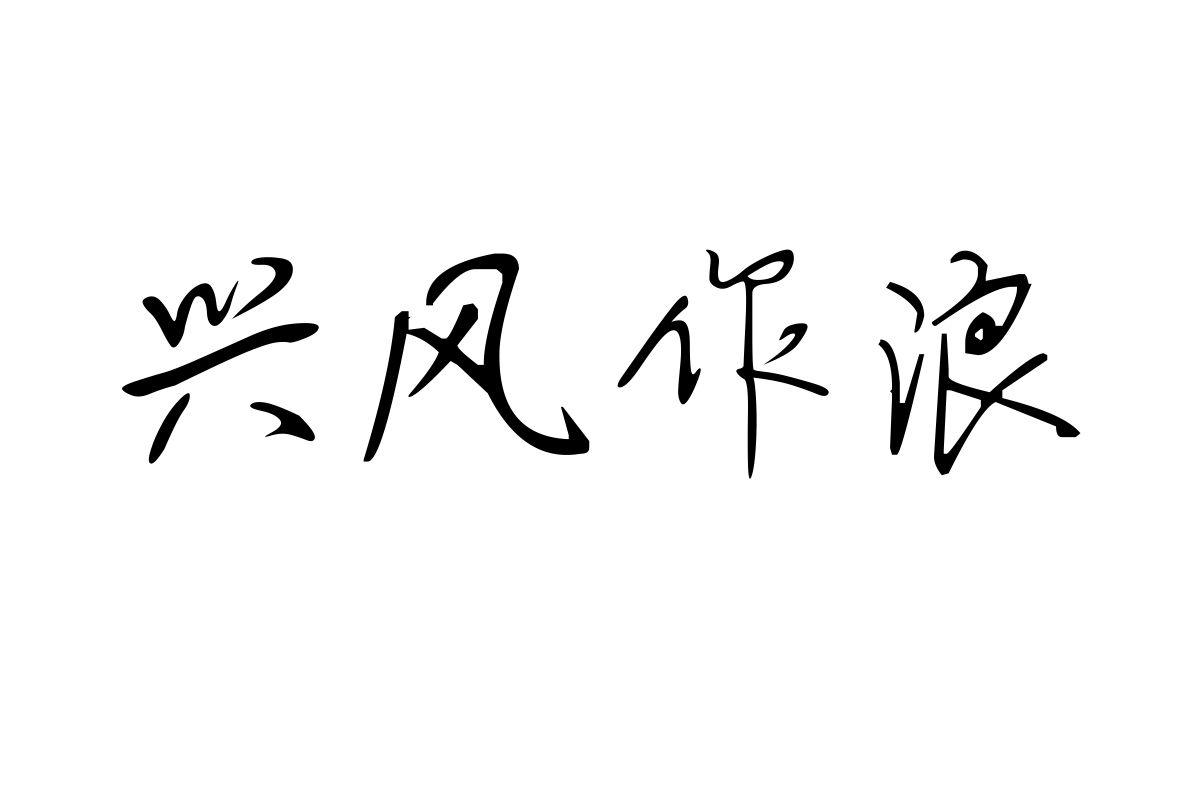
汉标灵芝体是一款具有独特风格的字体,它以灵芝为灵感,将灵芝的形态、纹理和色彩融入字体设计中。这款字体线条流畅、结构紧凑,给人一种自然、健康的感觉。
汉标灵芝体的字体特点如下:
1. 线条流畅:汉标灵芝体的线条简洁明了,没有过多的装饰,给人一种干净利落的感觉。
2. 结构紧凑:汉标灵芝体的字形紧凑,笔画之间留有适当的间距,使得整体看起来更加和谐。
3. 自然风格:汉标灵芝体借鉴了灵芝的自然形态,使得字体呈现出一种独特的自然风格。
4. 色彩丰富:汉标灵芝体的字体颜色丰富多样,可以根据需要进行选择和搭配,满足不同场合的需求。
5. 可定制性强:汉标灵芝体支持多种字号和样式,用户可以根据自己的需求进行定制,打造出个性化的字体效果。
总之,汉标灵芝体是一款具有独特风格和实用性的字体,适用于各种应用场景,如广告设计、包装设计、网页设计等。